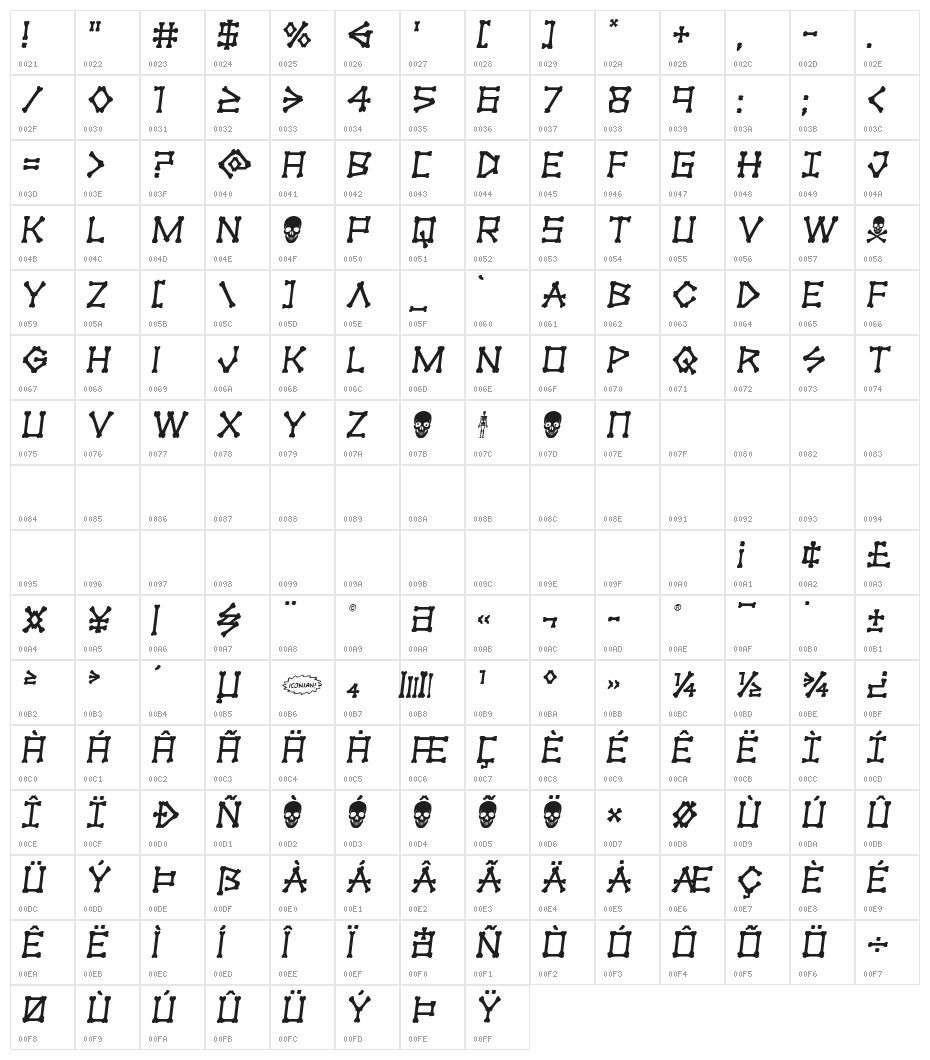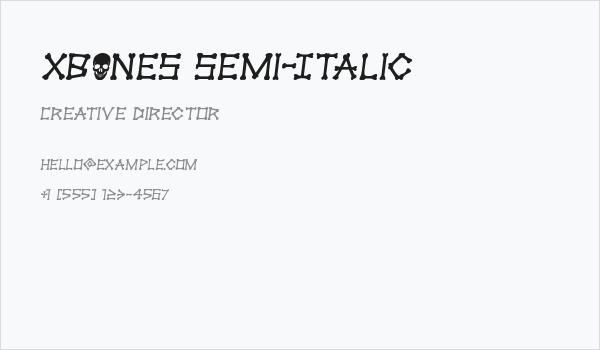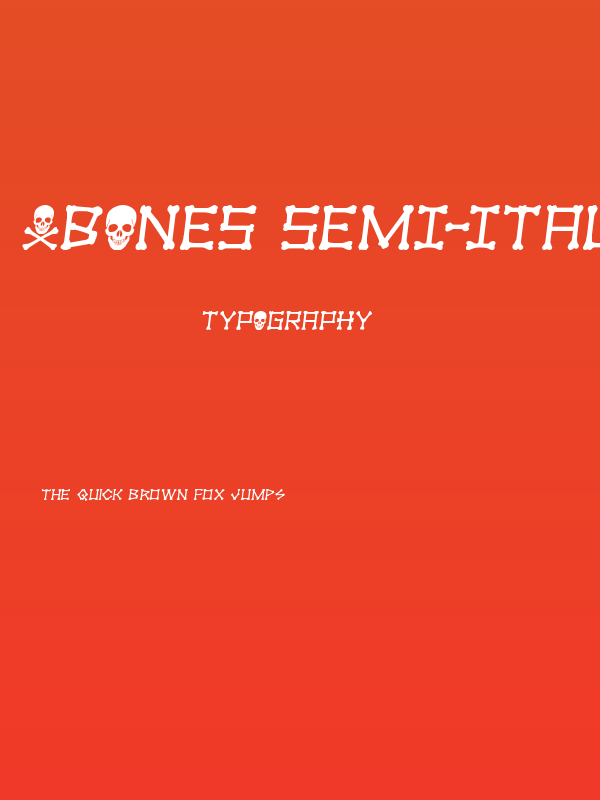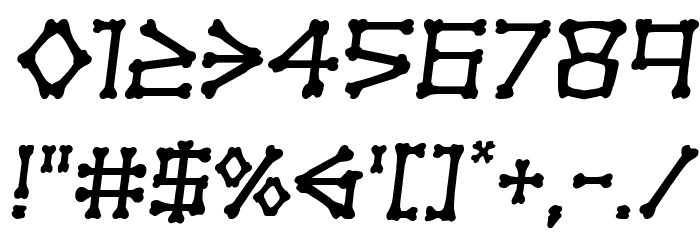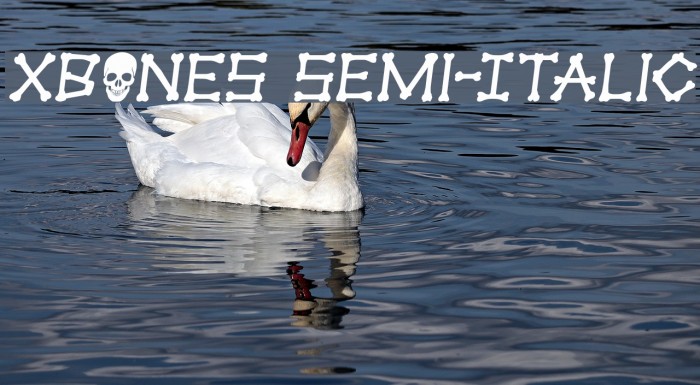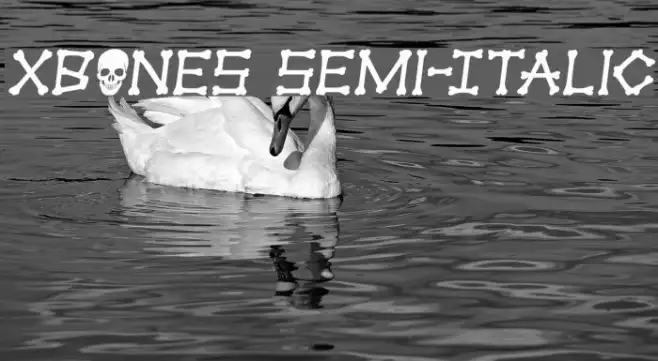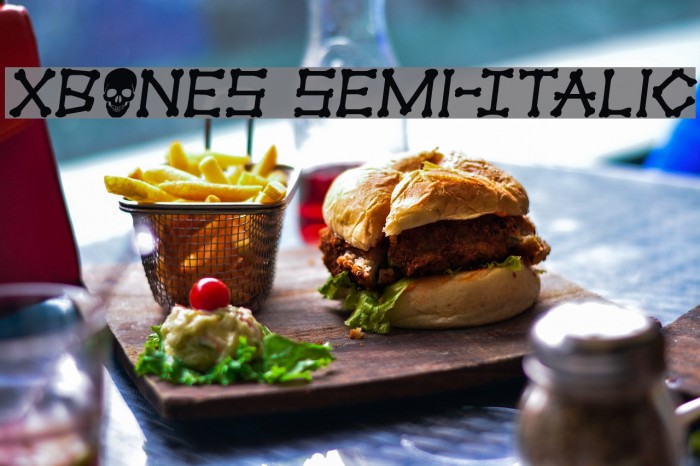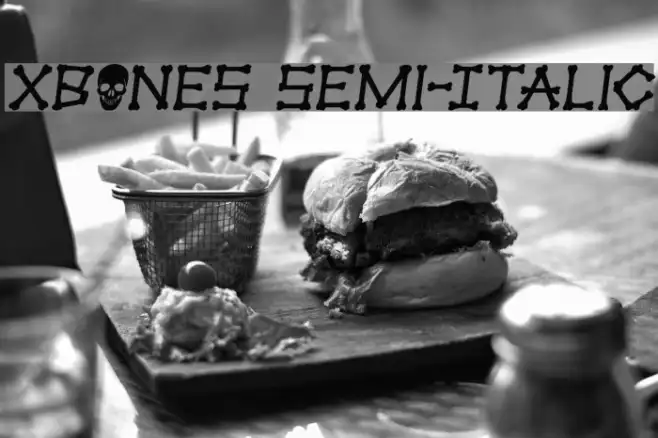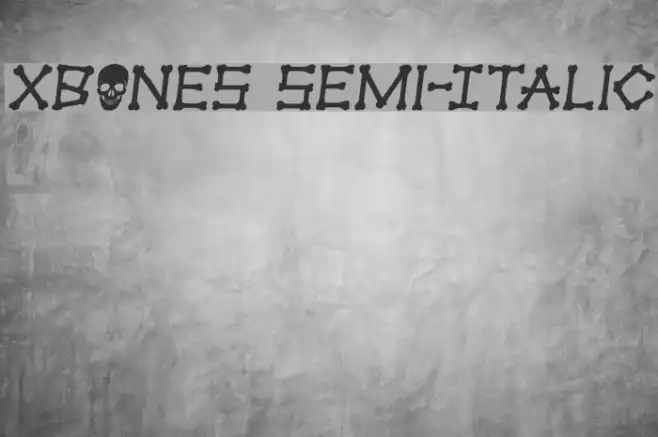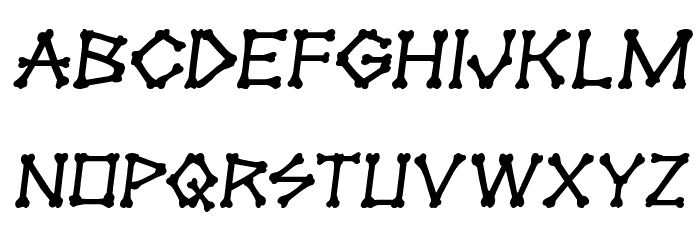
xBONES Semi-Italic Font
| Anwendungsfall | Headlines, Logos, Themed Events |
| Vorgeschlagene Projekte | Ideal for Halloween invitations, themed party decorations, children's book titles, and creative posters. |